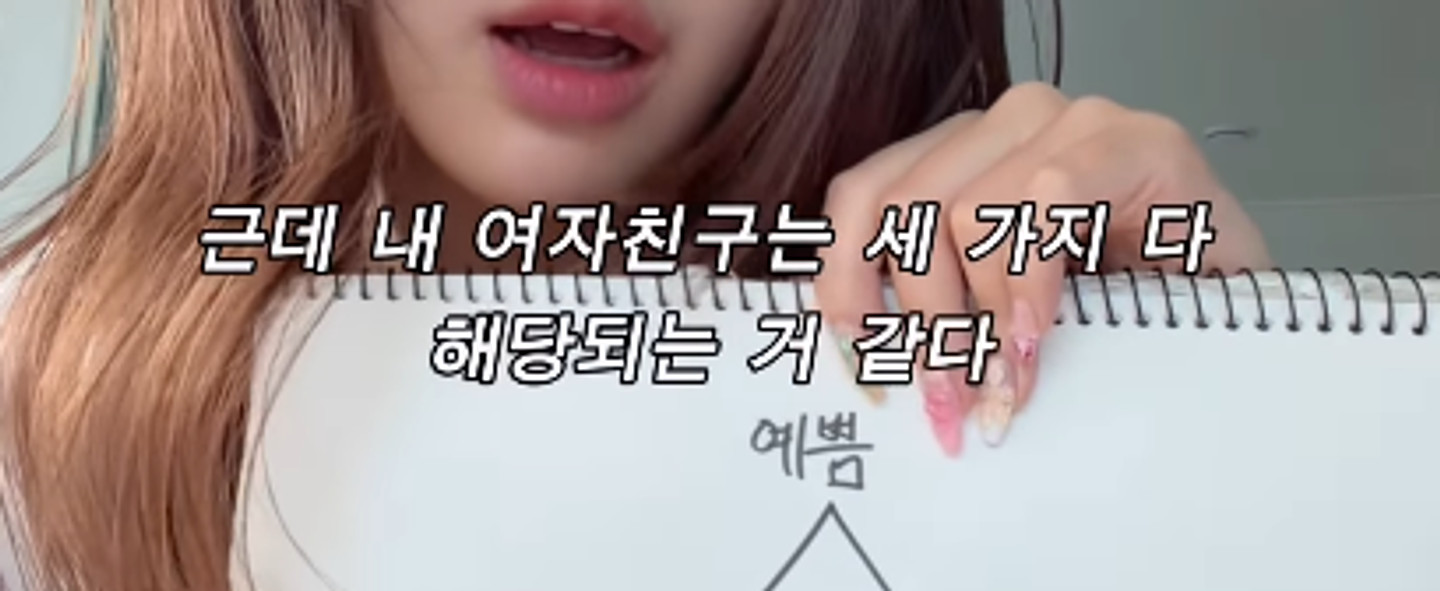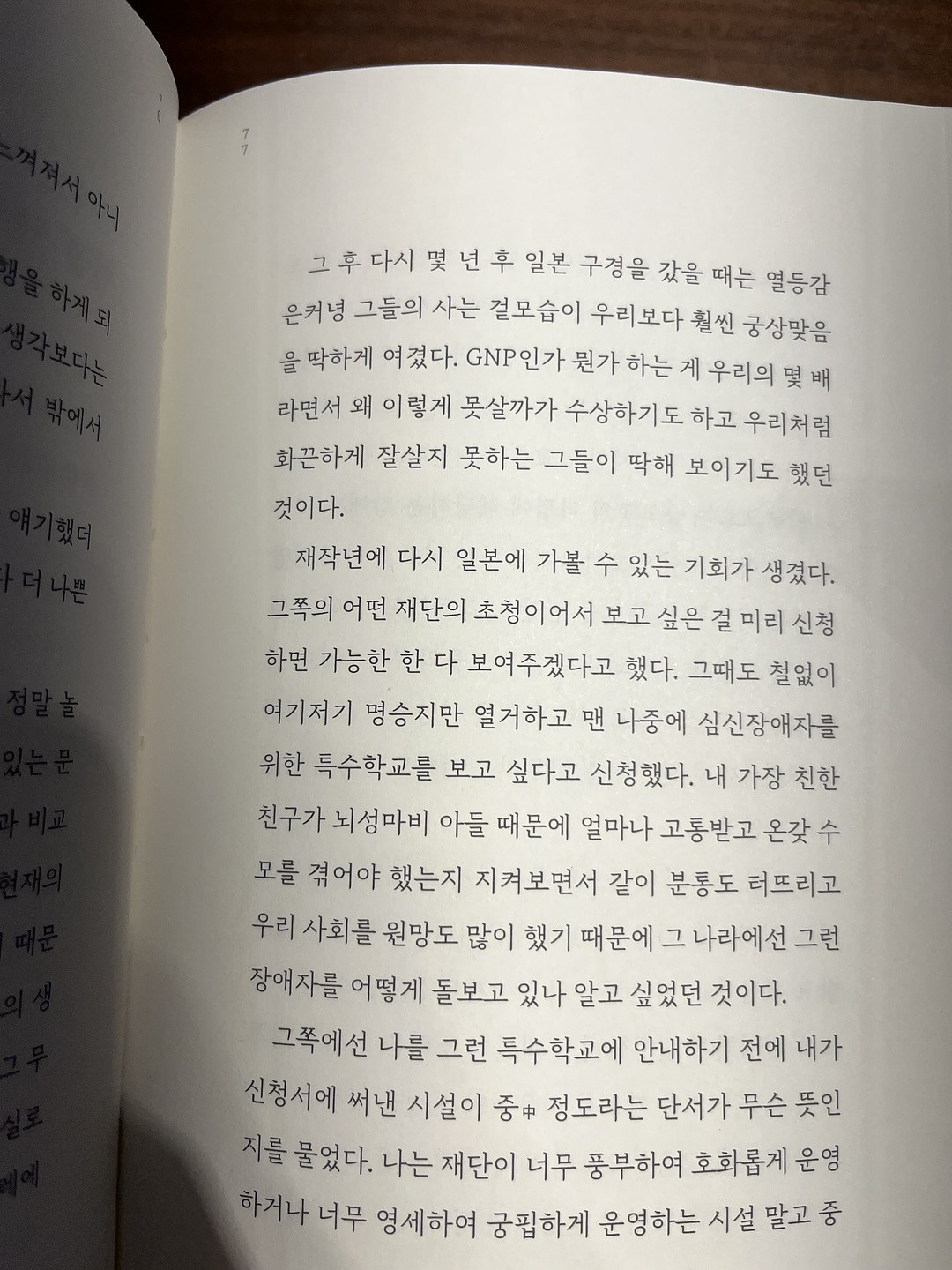
G마켓
Gmarket Sans
이 폰트 혹시 아시는 분 계신가요?? 정확한 폰트 알려주시면 좋은데 비슷하게라도 알고 계신 분 계시면 꼭 답변 부탁드립니당ㅠㅠ
고독한 미식가에 나오는 약간 기울여 진 동글동글한 글씨체는 뭔가요 감성계 브이로그 YouTube에서도 많이 보이더라구요